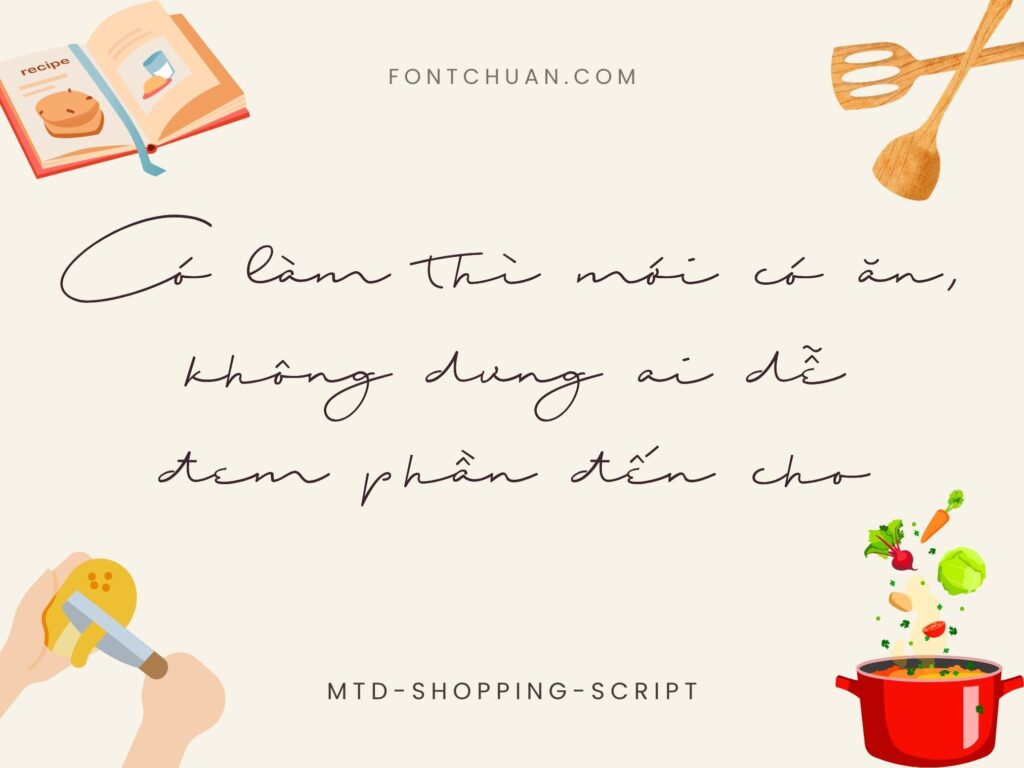
Font MTD Shopping Script Việt Hóa
Tác giả Font: Roland Hüse Design
Font MTD Shopping Script là một kiểu chữ viết tay mang phong cách chữ ký tự nhiên, được thiết kế bởi Roland Huse và đã được Việt hóa bởi Mộc Hạ. Font này hỗ trợ đầy đủ tiếng Việt cùng hơn 90 ngôn ngữ khác, mở rộng khả năng ứng dụng trong các thiết kế đa ngôn ngữ. Đây là một trong những phông chữ được cộng đồng thiết kế đánh giá cao và sử dụng trong nhiều dự án sáng tạo, đáp ứng nhu cầu đa dạng của người dùng.
MTD Shopping Script nổi bật với các đường nét mềm mại và uyển chuyển, mang đến cảm giác thân thiện và gần gũi. Font rất phù hợp cho các thiết kế logo, tiêu đề, bao bì sản phẩm, thiệp mời và các ấn phẩm đòi hỏi sự tinh tế và nghệ thuật. Các ngành nghề phù hợp bao gồm quảng cáo, giáo dục, công nghệ, thiệp cưới và ảnh cưới. Font này cũng lý tưởng cho các sự kiện như Tết, Giáng sinh, Valentine và các lễ hội khác.